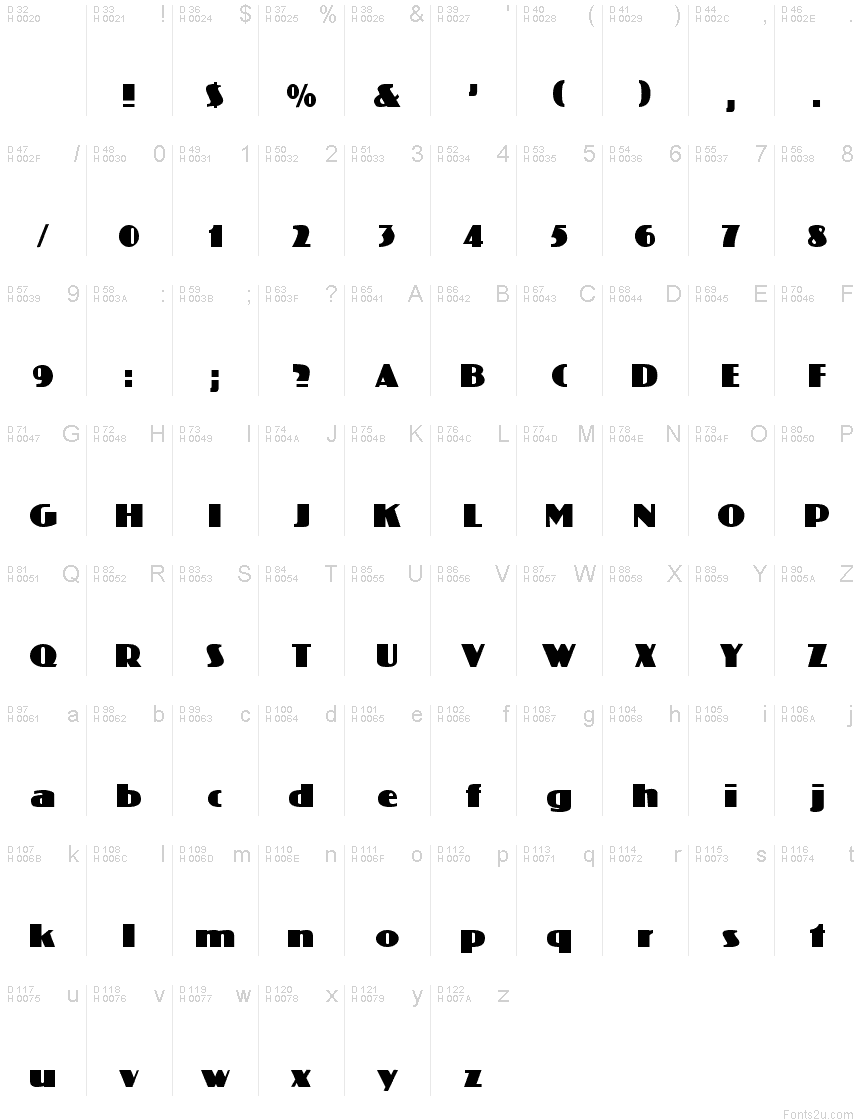
Coliseo to darmowy krój display w stylu retro, wyróżniający się grubymi, "atramentowymi" kształtami i charakterystycznymi, owalnymi oczkami, które przywodzą na myśl szyldy z lat 60. Jego pełne krągłości, ciasne światła i pionowa, masywna litera „l” budują wyrazisty, niemal rzeźbiarski rytm, który natychmiast przyciąga wzrok. W większym rozmiarze litery sprawiają wrażenie wyciętych z winylu lub ręcznie malowanych szyldów, nadając projektom analogowy, namacalny charakter.
Coliseo świetnie sprawdzi się na plakatach, śmiałych nagłówkach, logotypach w stylu vintage, okładkach albumów czy ulotkach eventowych, gdzie liczy się efektowna i zabawna forma. Dzięki dużej grubości i zaokrągleniom nawet krótkie słowa wyglądają jak gotowe logotypy, zwłaszcza w zestawieniu z kontrastowymi kolorami. W mniejszych rozmiarach warto połączyć Coliseo z prostym, geometrycznym krojem bezszeryfowym – dzięki temu zachowasz czytelność, a jednocześnie pozwolisz retro literom grać główną rolę.